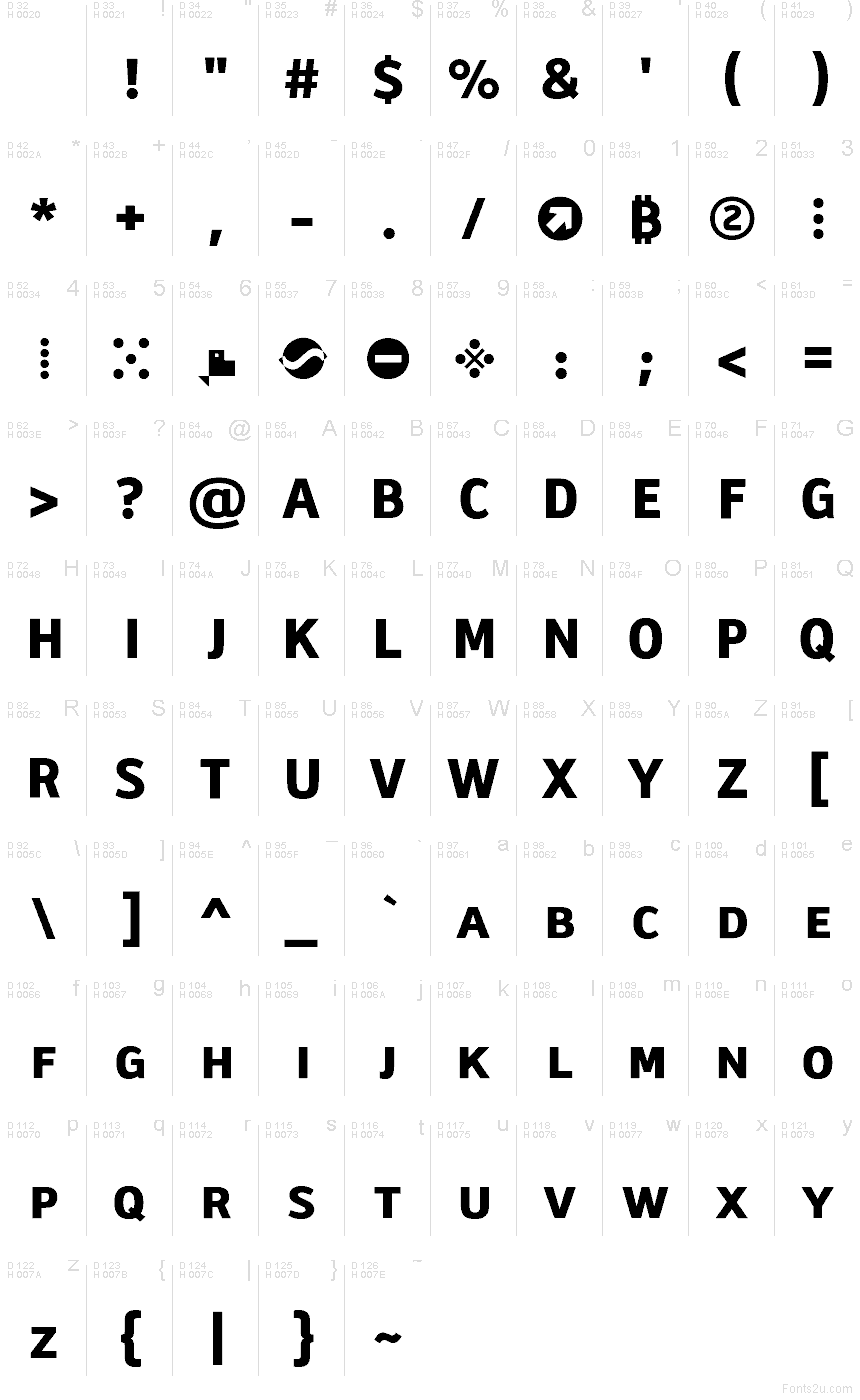
Biotrip Caps Bold di deFharo è un font sans serif gratuito in tutto maiuscolo, caratterizzato da un look diretto e dal sapore fantascientifico. Le lettere appaiono massicce e compatte, costruite con tratti ampi, angoli morbidi e grandi forme circolari che conferiscono al font un'atmosfera sci-fi accogliente, evitando quella freddezza tipica delle geometrie pure.
È ideale per poster, brand di videogiochi, copertine di album, grafiche per eventi tecnologici e brevi titoli che richiedono un tocco retro-futurista. Essendo un font gratuito, è perfetto anche per headline, loghi e monogrammi, poiché queste maiuscole arrotondate e piene rendono al meglio quando il testo è essenziale.
Biotrip Sans Caps is a multipurpose typeface, refined down to the last detail. It includes seven weightsLight, Regular, Medium, Semi Bold, Bold, Extra Bold, and Blackthat allow for the creation of solid, adaptable, and expressive visual systems.
Each variant has been carefully designed to preserve the humanist essence of Biotrip Sans, with the authority of capital letters.